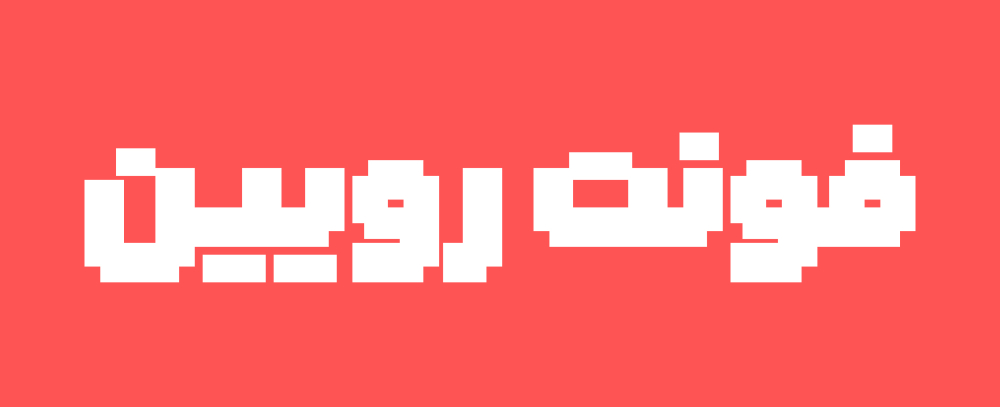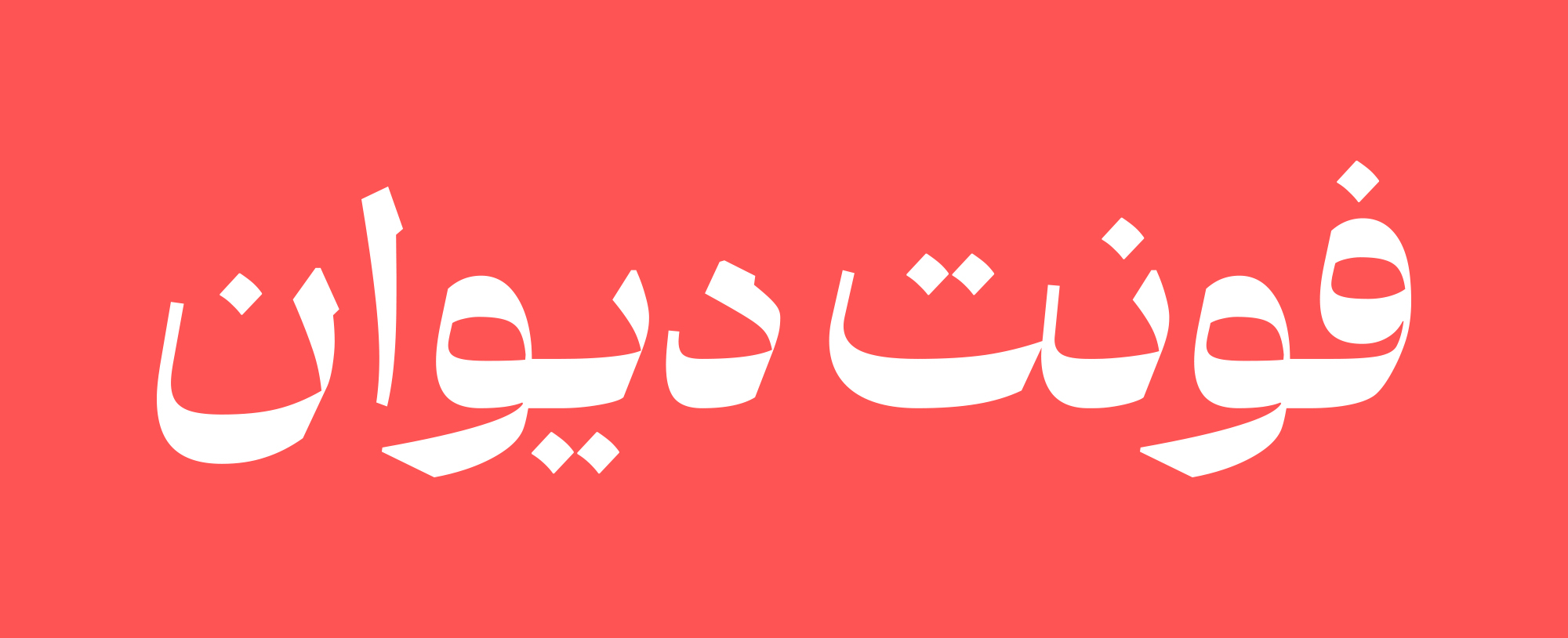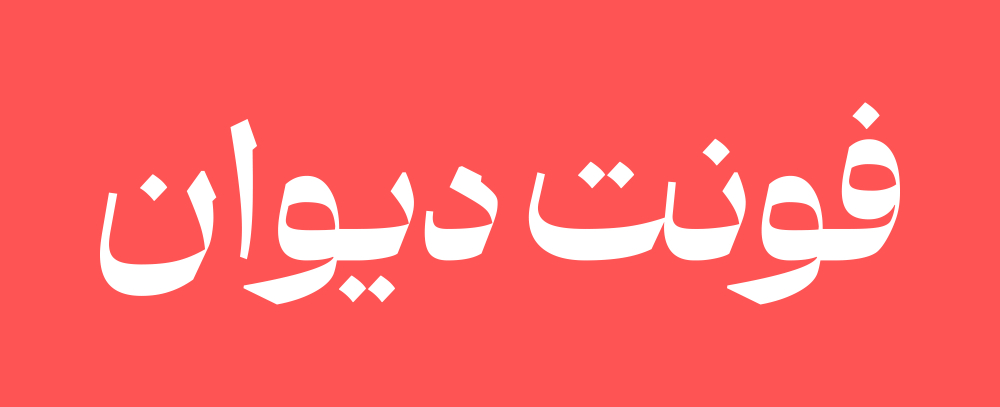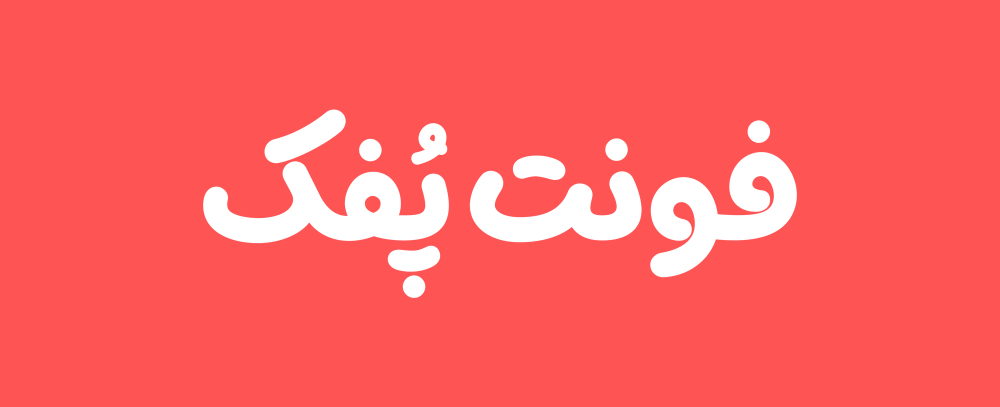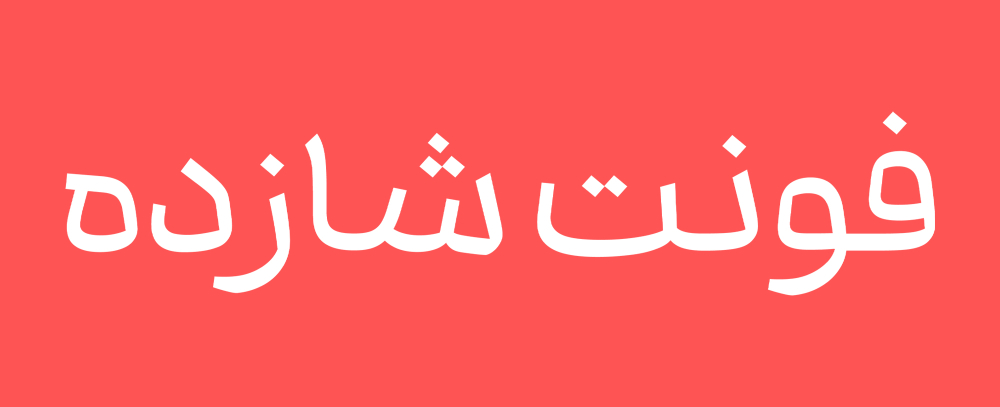
فونت دیوان با وقار و اصیل است و با روحیهٔ قاطع و متین خود، نقطه تلاقی بین گذشته باشکوه و حالِ پُرظرافت است.
این فونت تک وزن نمایشی با کنتراست بالا، بازآفرینی جسورانهای از روح خط ثلث است که با ظرافت، از ساختار خط نسخ پیروی میکند.
فونت دیوان با پشتیبانی از زبانهای فارسی، تورکی، عربی، اردو، کوردی و جاوی، گزینهای بیهمتا برای طراحان خوشذوق در پروژههای فرهنگی، هنری، ادبی و سنتی است و در طراحی تیترها، عناوین، متنهای کوتاه تبلیغاتی، پوستر، کاور، جلد کتاب و... کاربرد دارد.
در فونت دیوان هویت خط، با نوآوری معاصر دست در دست هم دادهاند تا نوشتار را به یک اثر هنری بدل کنند.
شازده، یک تایپفیس مدرن فارسی _ عربی است که بهصورت ویژه برای کاربردهای دیجیتال طراحی شده است. از ابتدا تمرکز آن بر وضوح، خوانایی و عملکرد بالا در محیطهایی مانند وبسایتها، رابطهای کاربری، اپلیکیشنها و متنهای طولانی بوده است. شازده حتی در اندازههای بسیار کوچک، کیفیت بصری خود را حفظ میکند و بدون افت وضوح، تجربهای روان و خوشخوان ارائه میدهد.
در روند طراحی، حروفی مانند «الف» و «لام» با ارتفاعی کوتاه و کنترلشده اجرا شدهاند. این تصمیم باعث شده تا فضای عمودی متن فشردهتر شود و تراکم خطوط کاهش یابد، بدون آنکه به خوانایی لطمهای وارد شود. همین ویژگی، متن را در نمایشگرهای کوچک یا تراکمهای بالا (High-DPI) خواناتر و کاربردیتر میکند.
فرم کلی حروف با ساختاری نزدیک به مونولاین طراحی شده است؛ ترکیبی دقیق از نرمی خط، تعادل هندسی و تأثیرپذیری هوشمندانه از ساختار خط نسخ. هر گلیف بهگونهای طراحی شده که در محدودهی خود بهخوبی قرار گیرد، و این دقت، چیدمان متن را در سیستمهای مبتنی بر گرید منظم و سازگار نگه میدارد.
در نتیجه، فونت شازده نهتنها در اندازههای ریز عملکردی عالی دارد، بلکه در متنهای بلند، مقالات دیجیتال و رابطهای کاربری پیچیده نیز ظاهر ساختارمند، یکدست و حرفهای خود را حفظ میکند. تلفیق زیباییشناسی معاصر با اصول سنتی تایپوگرافی فارسی و عربی، شازده را به انتخابی مطمئن برای طراحان وب، توسعهدهندگان رابط و ناشران دیجیتال تبدیل کرده است.
فونت رویین تلاشی است برای استفاده از هنر پیکسلی در طراحی حروف فارسی.
ساخت فونتی که حس و حال فونت های پیکسلی را بدهد و برای خواندن زبان فارسی راحت باشد، کار سختی است که رویین آن را ممکن کرده است. ساختار رویین شبیه به ساختار فونت های امروزی است و حس یک فونت مدرن را تداعی میکند.
پُفک یه فونت خوشخوراکه! خوراک هر چی که میخواید باحال و صمیمی بهنظر برسه؛ از موضوعات مربوط به تفریح، جشن و بازی گرفته تا تبلیغات خوراکیها و محتوای کودک و نوجوان.
پُفک شبیه فونتهای دستنویسه اما بصورت بداهه طراحی نشده. این فونت بر خلاف ظاهر رها و راحتش خیلی حساب شده طراحی شده تا در اندازههای ریز هم خوانا باشه.
اگه دنبال راهی هستید که حرفهای جدی رو با لحنی نرم و دوستانه بیان کنید، و خوانایی هم براتون مهمه، فونت پُفک بهترین انتخابه.
:: ۹ وزن متنوع از سبک تا سنگین
وزنهای پایین برای متنهای ریز و طولانی، وزنهای بالاتر مناسب عنوانهای تبلیغاتی.
:: مجموعهای گسترده از حروف و ترکیبات جایگزین
بیشتر جایگزینها بهصورت خودکار فعّال هستن. بخشی هم از طریق تنظیمات OpenType قابل کنترلند.
به کمک این جایگزینها میتونید:
اعداد انگلیسی رو فارسی کنید، تراز عمودیشون رو وسط چین کنید یا در لیستها، اعداد همعرض داشته باشید. همچنین میتونید شکل حروفی مثل «و»، «سش»، «ههه»، «حخجچ»، «کگ»، «ی»، و «دندانهها» رو تغییر بدید.
فونت شیوه یه فونت نمایشی سهحالته ست. اگه دنبال یک تیتر متفاوت، شجاع و خاص میگردی، شیوه همون چیزیه که لازم داری. شیوه سه تا استایل داره:
شیوه اصلاً برای متنهای بلند ساخته نشده. فونتیه که باید در چند کلمه بدرخشه، بزنه تو چشم و رد شه. اگه دنبال یه فونت تیتر برای پوستر، کاور، برند یا طراحی جسورانه هستی، شیوه خودش یه استایله.
فونت شیوه، الهامش از فرمهای نسخ سنتی بوده ولی اونقدر باهاش بازی شده که تبدیل به یه فونت خشن، خاص و گرافیکی شده. اینجا دیگه خبری از تعادل و خونسردی نیست. هر استایلش یه شخصیت جدا داره، ولی همشون یه چیز مشترک دارن: دیده شدن.